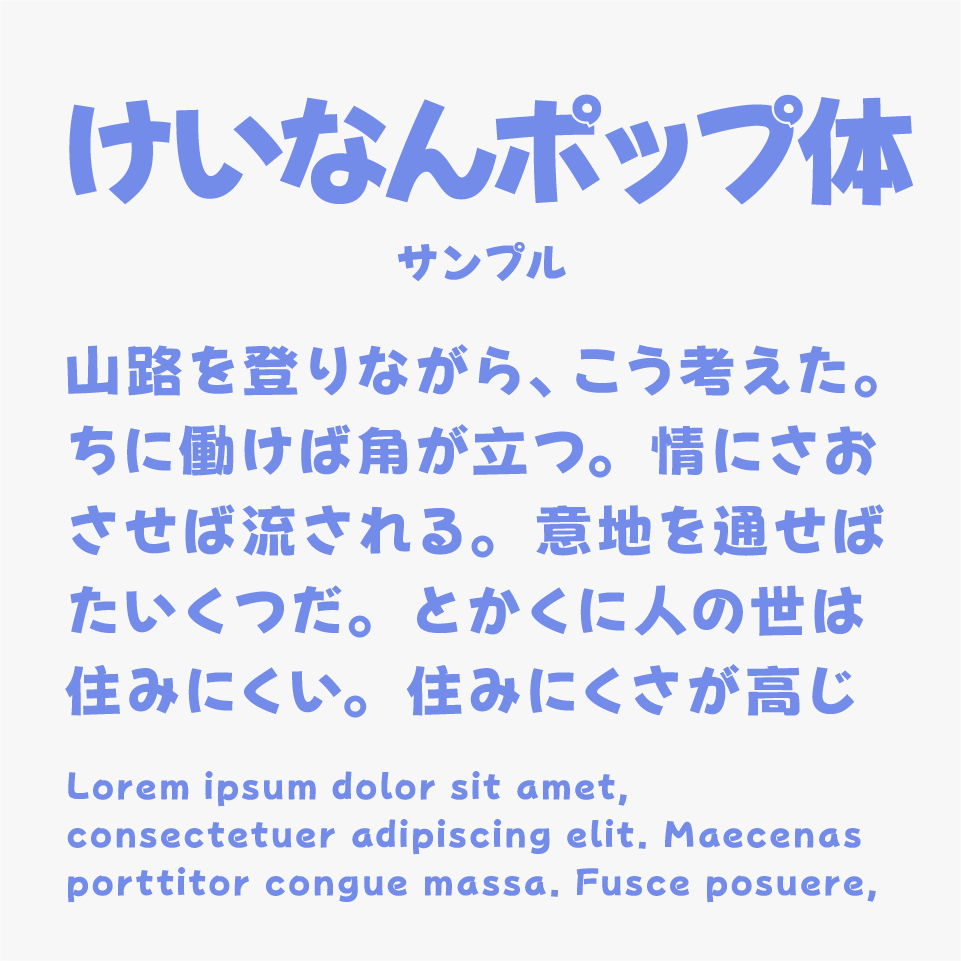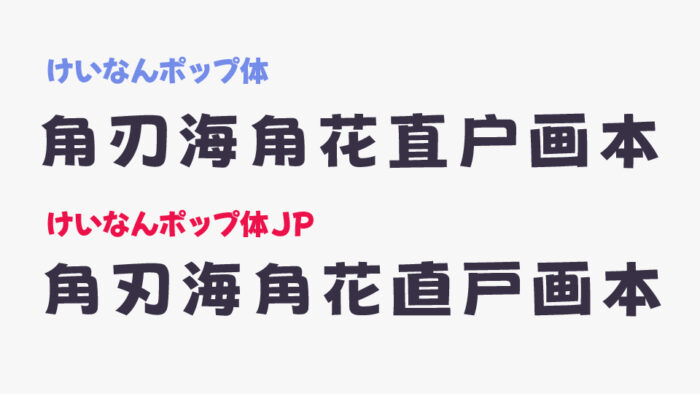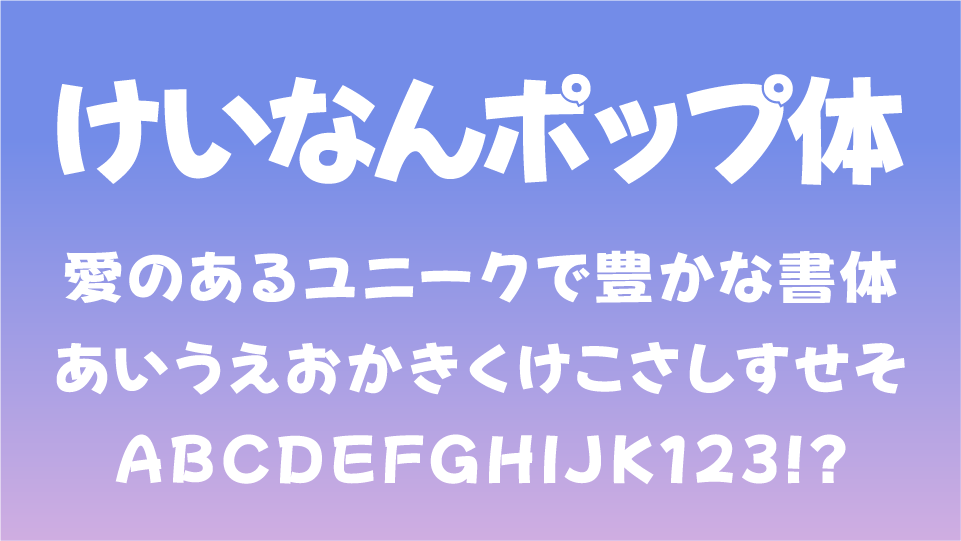
けいなんポップ体フォントは、「源暎ぽっぷる」フォントと「荆南波波黑」フォントを混植・加工して制作されたポップ体フォントです。
手描き風の丸みと、弾むようなリズム感が親しみやすい印象を与え、楽しそうな雰囲気をもつ可愛らしいフォントとなっています。
一部の漢字が、日本語の標準字形と異なるものがあり、それらの字形が調整された「けいなんポップ体JP」フォントもリリースされています。